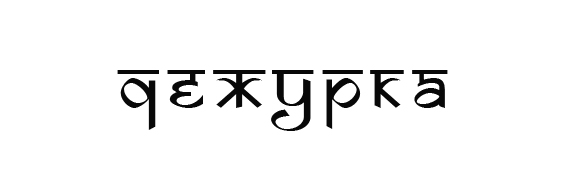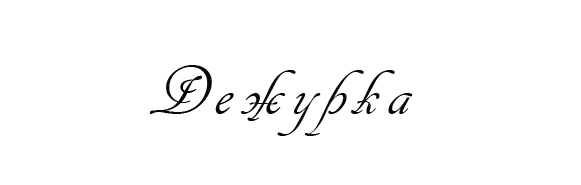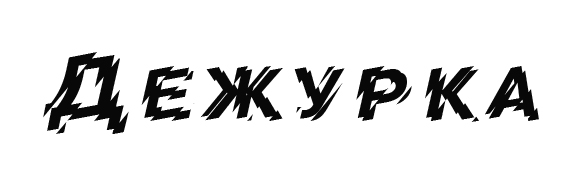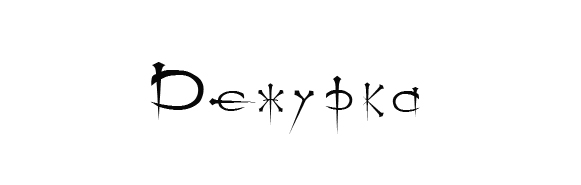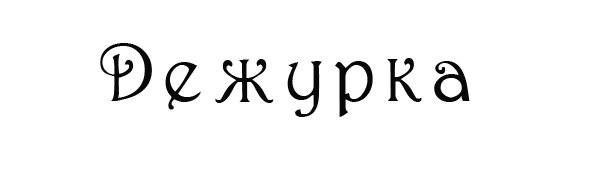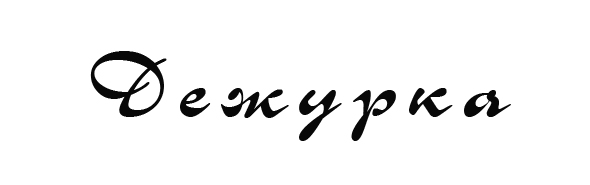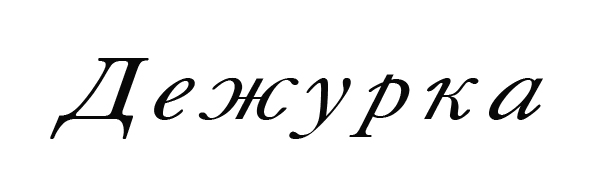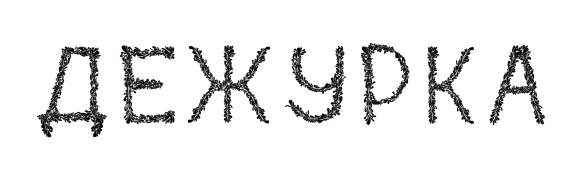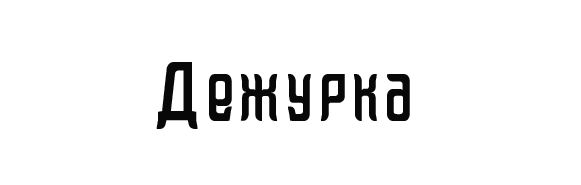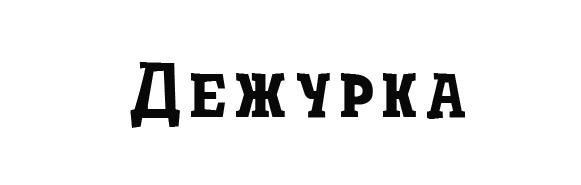
Бесплатные кириллические шрифты
Русских шрифтов появляется не так уж и много. Сегодня мы подготовили для вас небольшую подборку из бесплатных шрифтов с поддержкой кириллицы, которые подойдут для использования в веб-дизайне или полиграфии. Шрифты сделаны в разных стилях. Возможно вы найдете что-то нужное для себя.
Kaori Typeface
CricketInlineShadow
Tot samyi Shrift
a_BraggaOtlSh
PerfoCone
Bardelin
DS Izmir Normal
Cancellaresca Script LET Plain1.0
Caslon
CorridaCTT
1 Nevrouz M
Ogilvie Cyr
Parisian
20 db
Otscookie
Hardpixel
Adine-Kirnberg
Cleopatra
a_CampusOtlSh-Bold
CricketHeavy
SkazkaForSerge
Половина шрифтов родом из СССР, причем весьма заезженные. Хотя парочка нормальных есть.